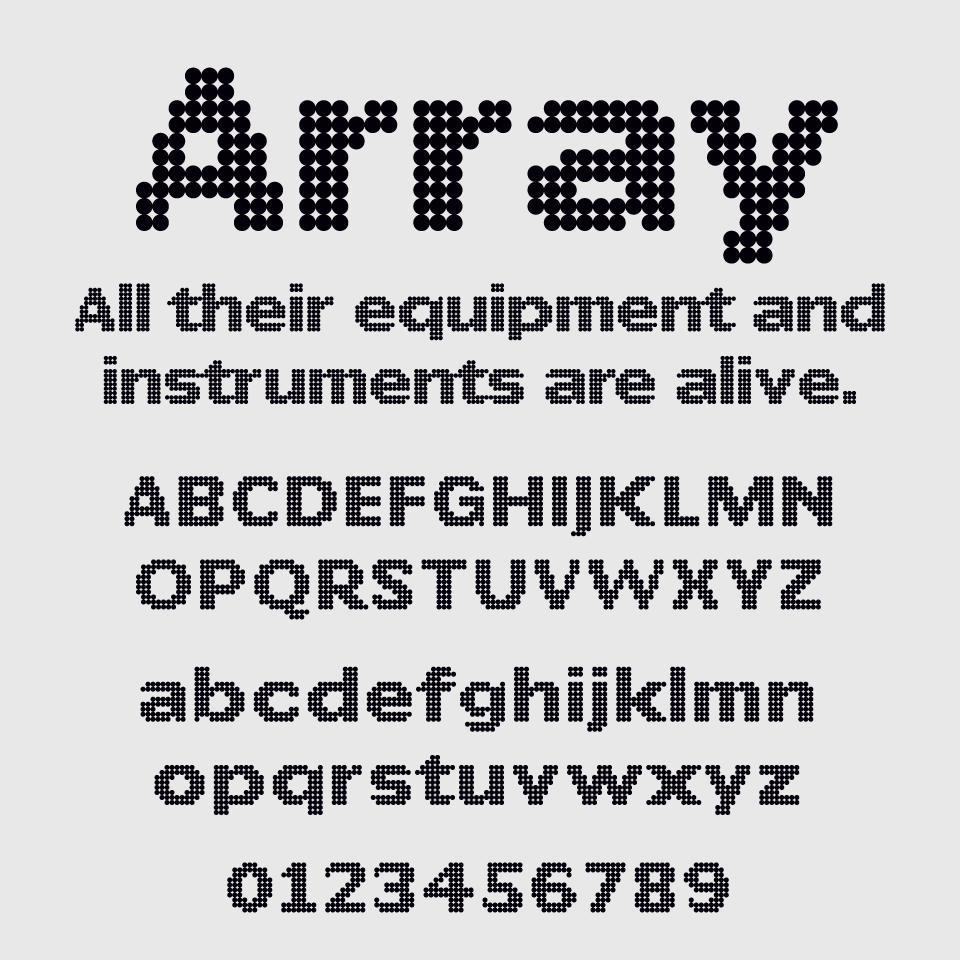
Arrayフォントは、小さなドットの集合で形作られた文字は、まるでLEDディスプレイや電光掲示板のような雰囲気のあるドット風フォントです。
緻密に作られたピクセル感がありながらも、柔らかな丸みを帯びていて、デジタルと親しみやすさを融合させたユニークなスタイルが特徴です。レトロなゲーム機や電子機器、テクノ系のグラフィックと相性が良いフォントです。
同じスタイルで、平体や長体にバリエーションも用意されているので、トーンにあわせて使い分けができるのも嬉しいポイントです。